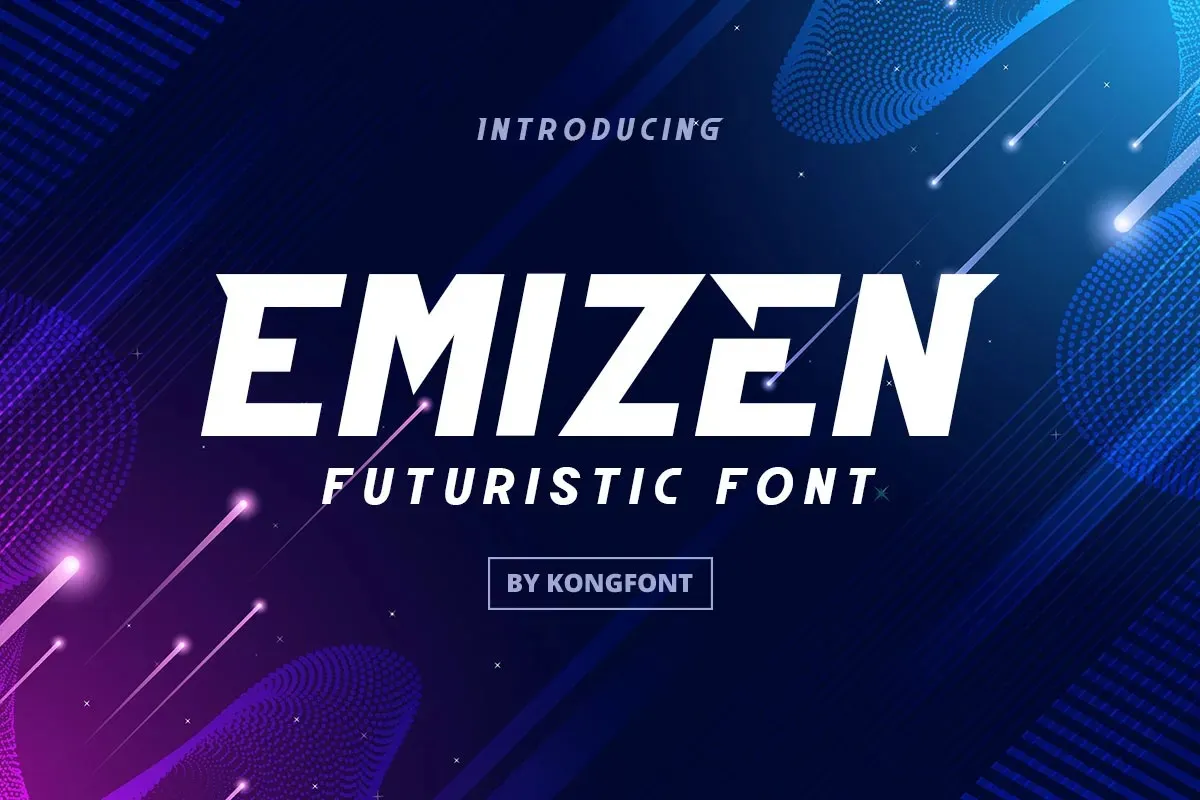
Emizen Font – Download Grátis
Emizen Font é uma escolha perfeita para aqueles que buscam uma fonte display moderna e ousada. Desenvolvida para criar ambientes vibrantes e criativos, esta fonte oferece um visual distintivo e sofisticado. Suas letras únicas proporcionam a sensação de elegância, simplicidade e modernidade prometidas. Perfeita tanto para aplicativos publicitários quanto para sublimação ou tênis personalizados, Emizen também é uma ótima escolha para elementos de automobilismo e entretenimento. Sua capacidade única de se adaptar a vários estilos cria soluções criativas que destacam seu design inovador em qualquer aplicação visual.